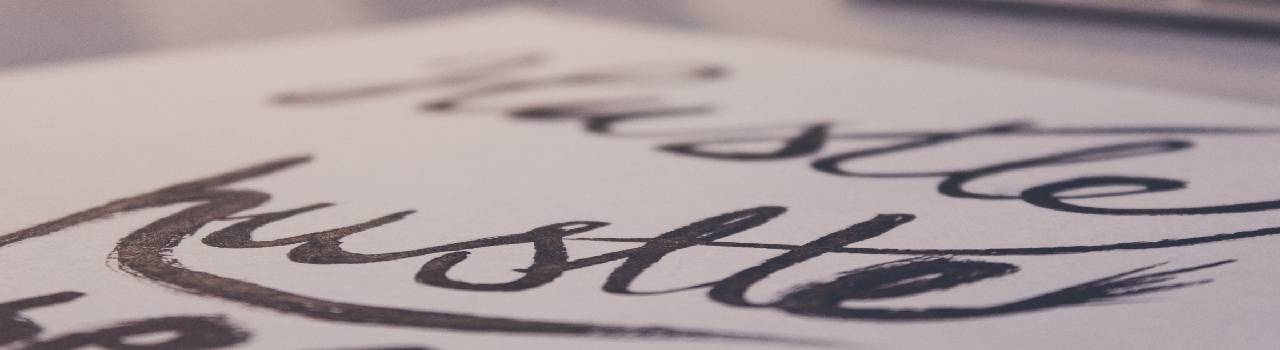
Si eres diseñador o tienes que hacer uso seguido de formatos como slides, seguramente has tenido que parar a pensar durante un buen tiempo cuál tipografía o font usar y luego de eso dónde conseguir una que cumpla esas características que estás buscando. ¿Te has imaginado que puedes crear esa font perfecta tú mismo?
¿Por qué crear una cuando puedes comprarla?
Aparte de que el proceso es divertidísimo y te sentirás constantemente como si estuvieras jugando (¡Puedes usar pinceles, marcadores de colores, lápices, cualquier cosa que escriba!), conseguirás con más facilidad imprimir el alma e identidad de tu marca porque, ¿quién sabe más que tú acerca de lo que estás creando?
El proceso de crear una tipografía
Hay una serie de pasos a respetar para lograr una tipografía de gran calidad:
- Caligrafía: Esta es la parte más ortodoxa y al tiempo la más experimental. Aprendiendo los fundamentos lograrás entender qué hace que una letra esté bien diseñada y qué hay que evitar.
- Anatomía: Aquí es donde se le da la personalidad a la tipografía. Aprendiendo sobre formas llenas, formas vacías, diferentes maneras de usar picos y vértices. Se experimenta respetando siempre la caligrafía.
- Vectorizar: Una vez que tienes definida tu tipografía la debes digitalizar. Es un proceso técnico que busca que el resultado sea exactamente igual a lo que dibujaste de manera análoga.
Software para vectorizar
Illustrator ha sido usado para vectorizar y crear tipografías, sin embargo existen otras opciones como Glyphs que fue creado específicamente para esta función.
Glyphs es muy recomendado puesto que su interfaz es más simple, puede ser personalizado por medio de scripts y plugins y también podrás automatizar muchas tareas, reciclando formas de letras que se repiten y teniendo una gran ayuda para completar todos los caracteres del abecedario que elijas.